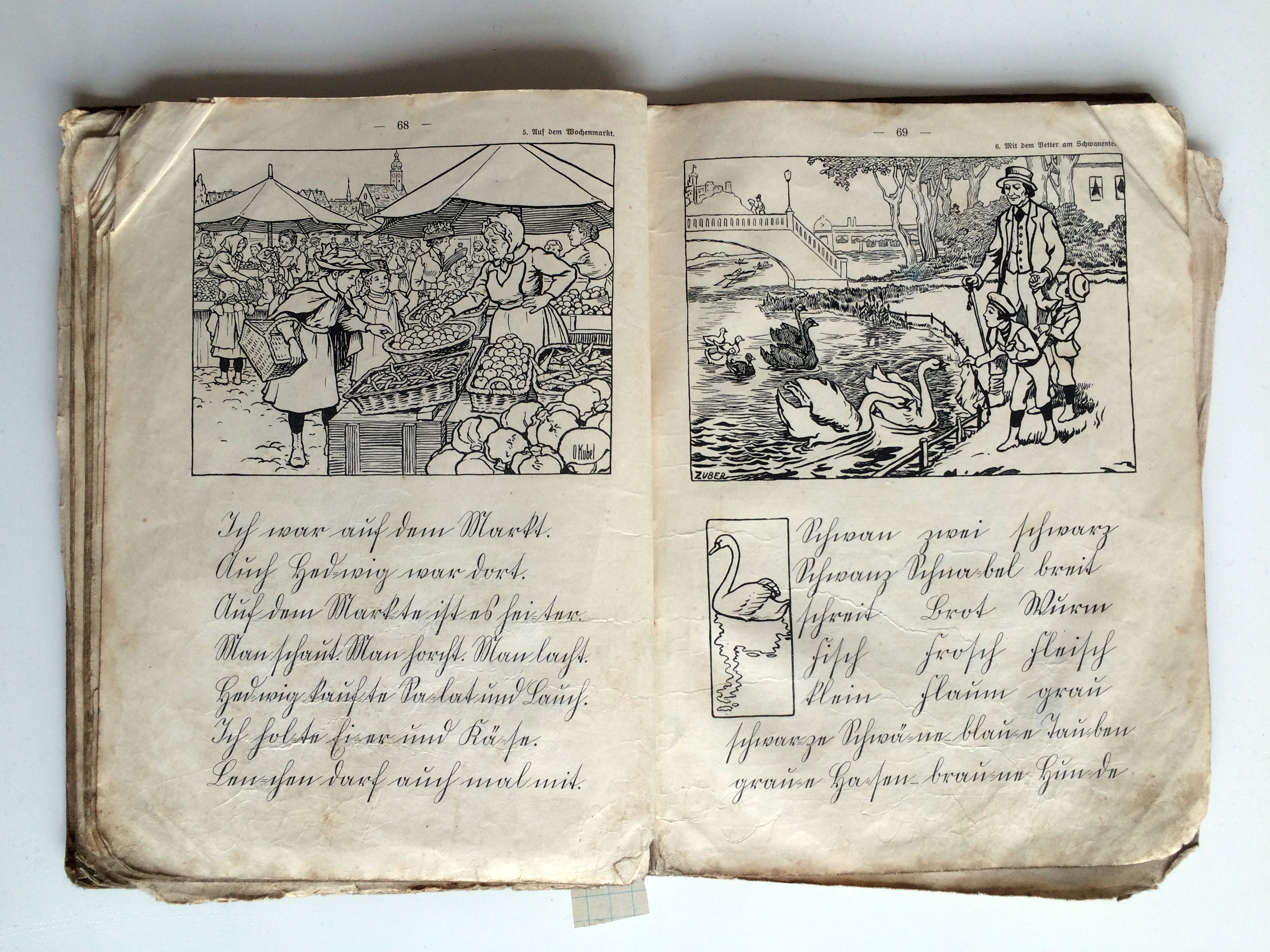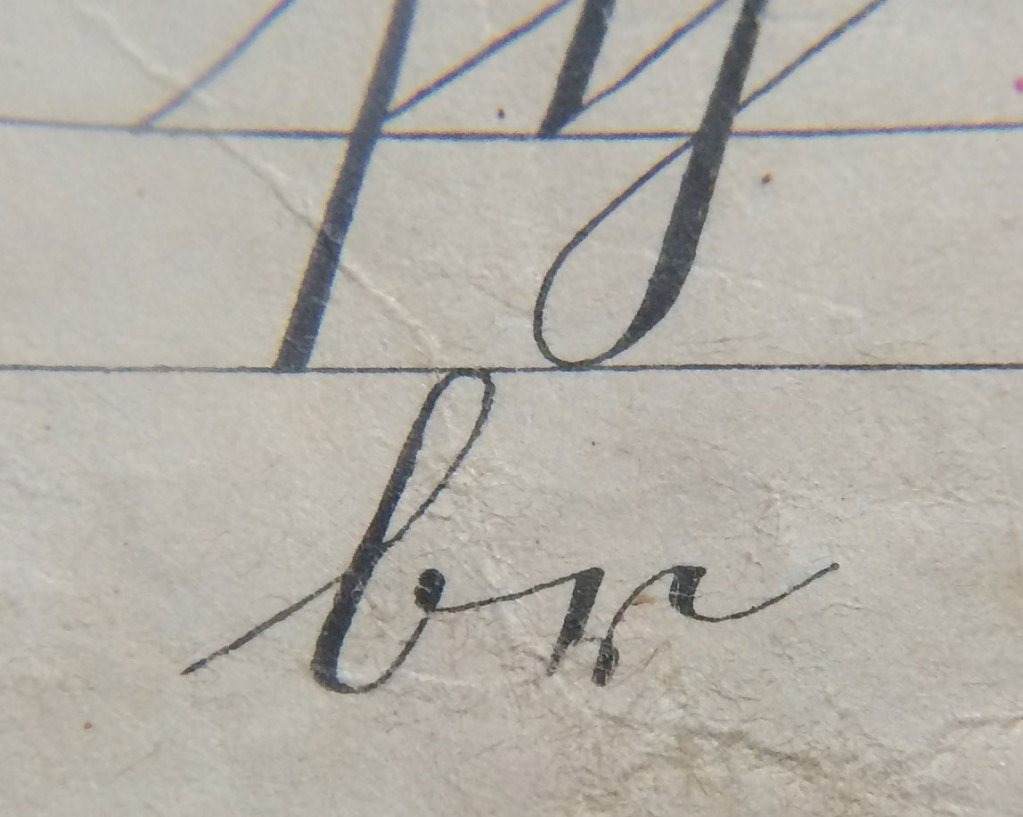
Kurrentsatz-Technik
Mein Freund und Kupferstecher!
Solche Kurrent-Fibeln waren in der Regel Kupferstiche, für große Auflagen auch Stahlstiche, die dann mir höchstwer Präzision direkt nach der gezeichneten Vorlage von Hand gestochen wurden. Die Kupferstecher dieser Zeit waren wirklich gut, und bekamen wirklich jeden Buchstaben nahezu 100%ig gleich hin.
Im Schreibunterricht vor Sütterlin mussten die Kinder ja noch "wie gestochen" schreiben lernen, schafften sie dies nicht, gab es Hiebe mit der Rute auf die ausgestreckten Finger. Dieses "wie Gestochen" war dabei auch sehr wörtlich gemeint, nämlich möglichst genau so wie der gedruckte Stich.
Meine Mutter hatte in den 1960er Jahren einen Antiquitätenhandel, und da habe ich so etwas oft im Original gesehen, und es war sehr deutlich erkennbar, dass es sich hier um Tiefdruck handelte.
So gesehen waren es eigentlich keine Reproduktionen, sondern letztlich Originale, die da gebunden wurden.
Im von Johann Friedrich Kiechel 1788 in Straßburg herausgegebenen Buch "Die teutsche Kurrent- Kanzlei und Fraktur-Schrift in einer theoretisch praktischen Anweisung, zum Gebrauch des Schul- und Privat-Unterrichts" konnte ich anhand der Signatur den Mainzer Kupferstecher Heinrich Hugo Cöntgen identifizieren. Auch viele später erschienenen Schreib-Lehrbüchern waren oft bekannte Kupferstecher im Einsatz.
Daher waren derartige Fibeln auch sehr teuer, und wurden dementspechend sehr vorsichtig zu nutzen, sodass sie durch die Hände vieler Schülergenerationen gehen konnten. Auch wurden sie dann nur in der Schule selbst genutzt.
Um das genau sehen zu können, müßte man mal eine Vergrößerung vor sich haben. Ich glaube nicht, daß diese Seiten von Stichen gedruckt wurden. Das sind keine Tiefdrucke. Ich wußte nicht, daß Fibeln jemals in Stichen gedruckt wurden. Warum soll das Buch auf dem Foto kein Buchdruckwerk sein?
Je länger ich da drauf starre: nicht vom Stich gedruckt. Radierung – kann ich kaum glauben. Vorlage geschrieben, Chemigrafie, Buchdruck, würde ich in Erwägung ziehen. Ist auf der Rückseite keine Schattierung zu sehen bei schrägem Lichteinfall? Nicht ein Hauch? Dann wäre es Flachdruck. Tiefdruck würde ich angesichts des Fotos ausschließen.
Und ich bin etwas ungläubig, daß Fibeln im Stahlstich gedruckt wurden. Wurde jemals überhaupt ein Buch im Stahlstich gedruckt? Das war doch ein Illustrationsdruckverfahren, für Einlagen.
Weil diese noch in klassischer Kurrentschrift hergestellten Fibeln aus einer Zeit stammen, wo es einfach noch keine photochemische Reproduktionstechnik gab.
Illustrationen in Büchern waren zu dieser Zeit oft Stiche, Farbtafeln Lithografien, und es gab durchaus Seiten mit gemischter Drucktechnik,also erst einmal den Tiefdruck der Illustrationen, die dann i9n einem 2.  Durchlauf damm mit Texten im Buchdruck bedruckt wurden.
Schließlich stammen diese Bücher aus einer Zeit, in der noch Daguerrotypien und erste Fotos auf nassen Collodium-Platten nur bei sehr viel Licht, mit minutenlanger Belichtung entstanden. Ab deen späteren 1880er Jahren wurden dann Reproduktionen von Kupferstich-Platten per Galvanoplastik möglich, und somit auch höhere Auflagen durchführbar.
Es gibt sicherlich sehr vieles, was ich nicht weiß. Von gemischtem Druck zum Beispiel. Auf die Rückseite von einem Stahlstich im Buchdruck drucken? Ich kann mir das nicht einmal vorstellen. Ich würde sogar sagen: Das geht nicht.
Ich glaube: Das auf dem Bild sind keine Tiefdrucke von Stichen. Ich würde keinen großen Betrag darauf verwetten, nur einen kleinen. Ralf, aus welchem Jahr ist das Buch?
Otto Kubel, der Illustrator des Bildes auf der linken Seite, lebte von 1868 bis 1951.
Dann müsste das rechte Bild von Julius Zuber, 1861–1910, sein.
Ich bleibe bei Buchdruck. Das ist ja dann wahrscheinlich um 1890/1900 gedruckt, und da konnte der Buchdruck alles. Ralf, wenn du das Buch hast und Detailaufnahmen machen willst, also Vergrößerungen, sowohl von den deckenden als auch den abgeschabten Stellen, kann man den Farbauftrag noch genauer sehen. Aber Stahlstichfarbe würde eher abplatzen als abreiben, glaube ich. Die Vorlagen: Ich weiß nicht, warum man sich die Mühe des Stechens für dieses Buch hätte machen sollen. Das ist ja nichts Wertvolles. Also geschrieben und reproduziert für den Buchdruck.
Ich hab bei einigen ähnlichen Abbildungen gelesen, dass das Holzstich sei. Vielleicht trifft das auch hier zu?
Man konnte mit Holzstich viel machen, es gab da chemische und mechanische Hilfsmittel. Aber ich würde die beiden Bilder nicht für Holzstiche halten und deshalb auch den Rest nicht. Das wäre doch auch arg aufwendig gewesen. Wozu der Aufwand, wenn man Klischees machen kann. Das konnte man damals. Ich weiß nicht, wann das losging, aber in den 1920er Jahren gab es den vierfarbigen Bilderdruck als Buchdruck, der es dann bald mit dem Rotationstiefdruck zu tun bekam.
Forumsteilnehmer gutenberger versteht von Bilderdruck mehr als ich. Vielleicht schaut er mal drauf?
Tiefdruck oder Stiche sind das kaum.